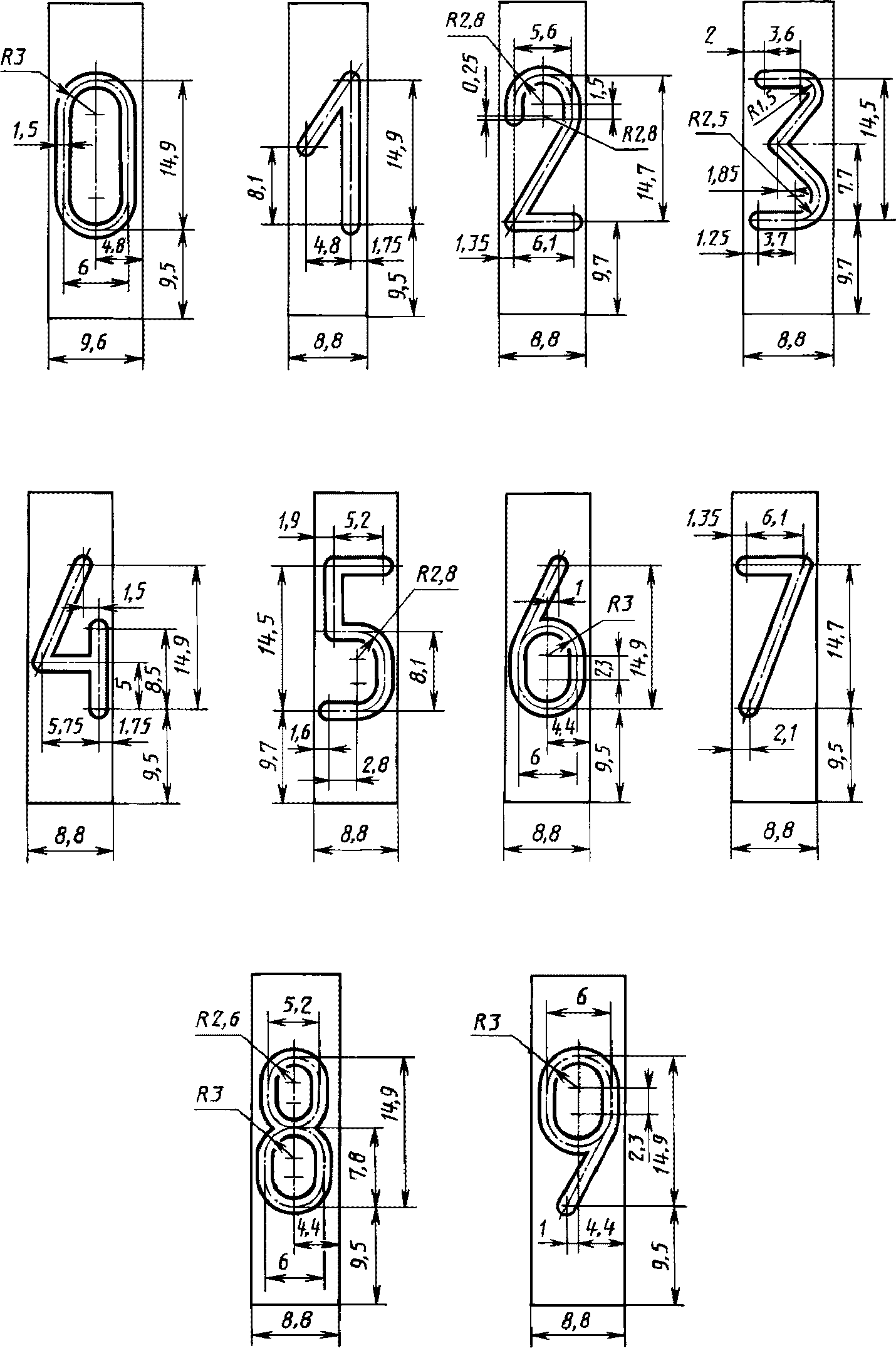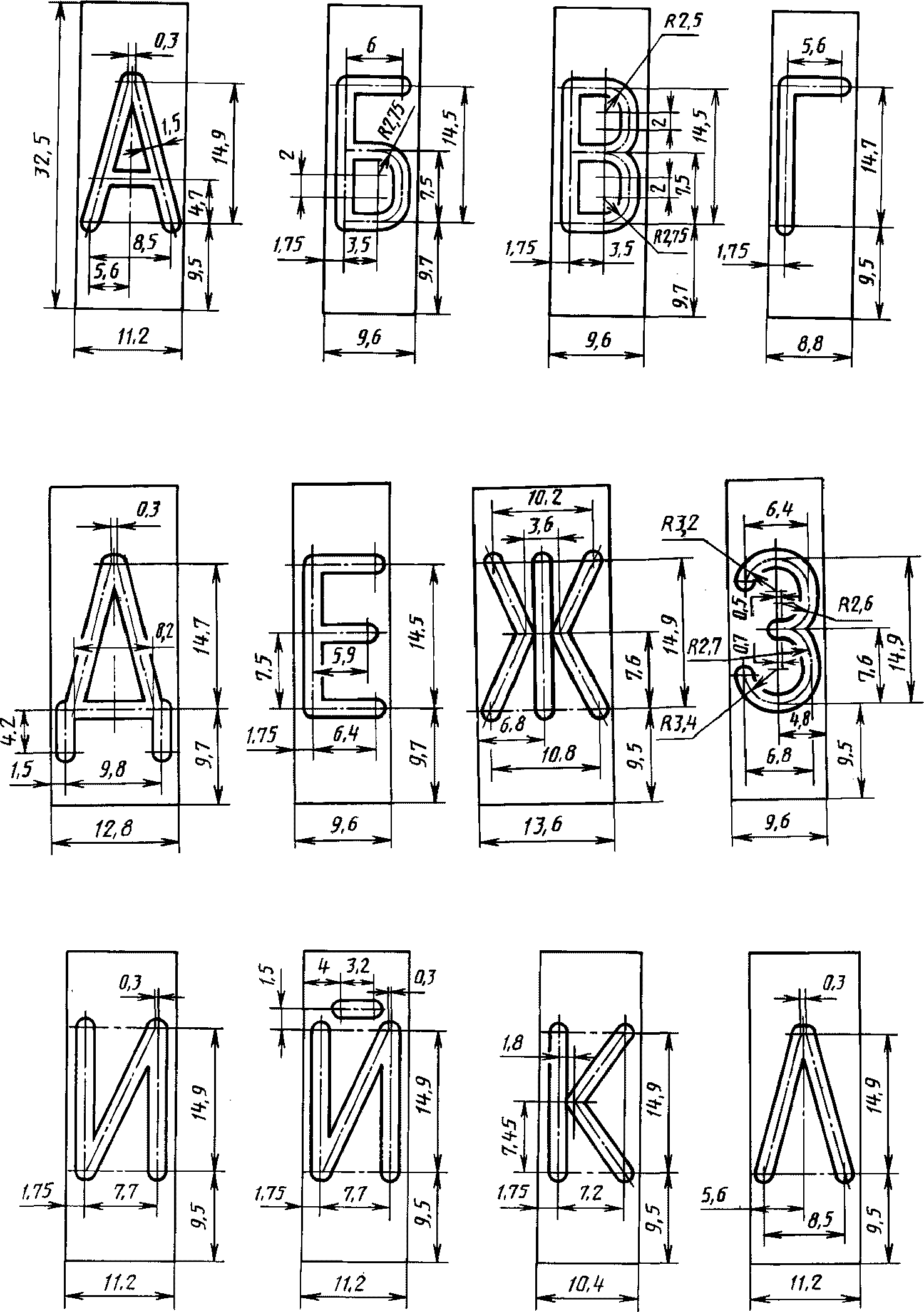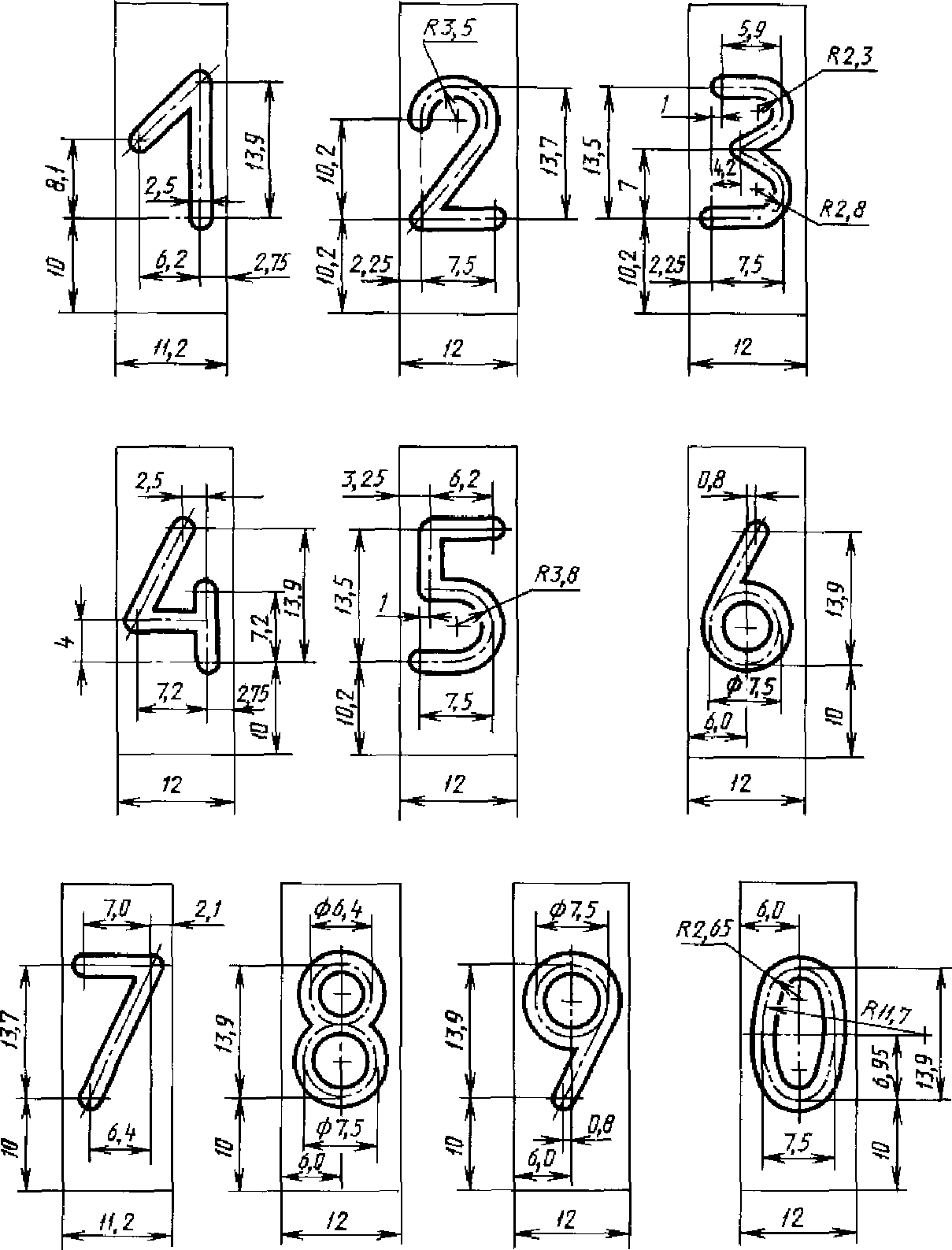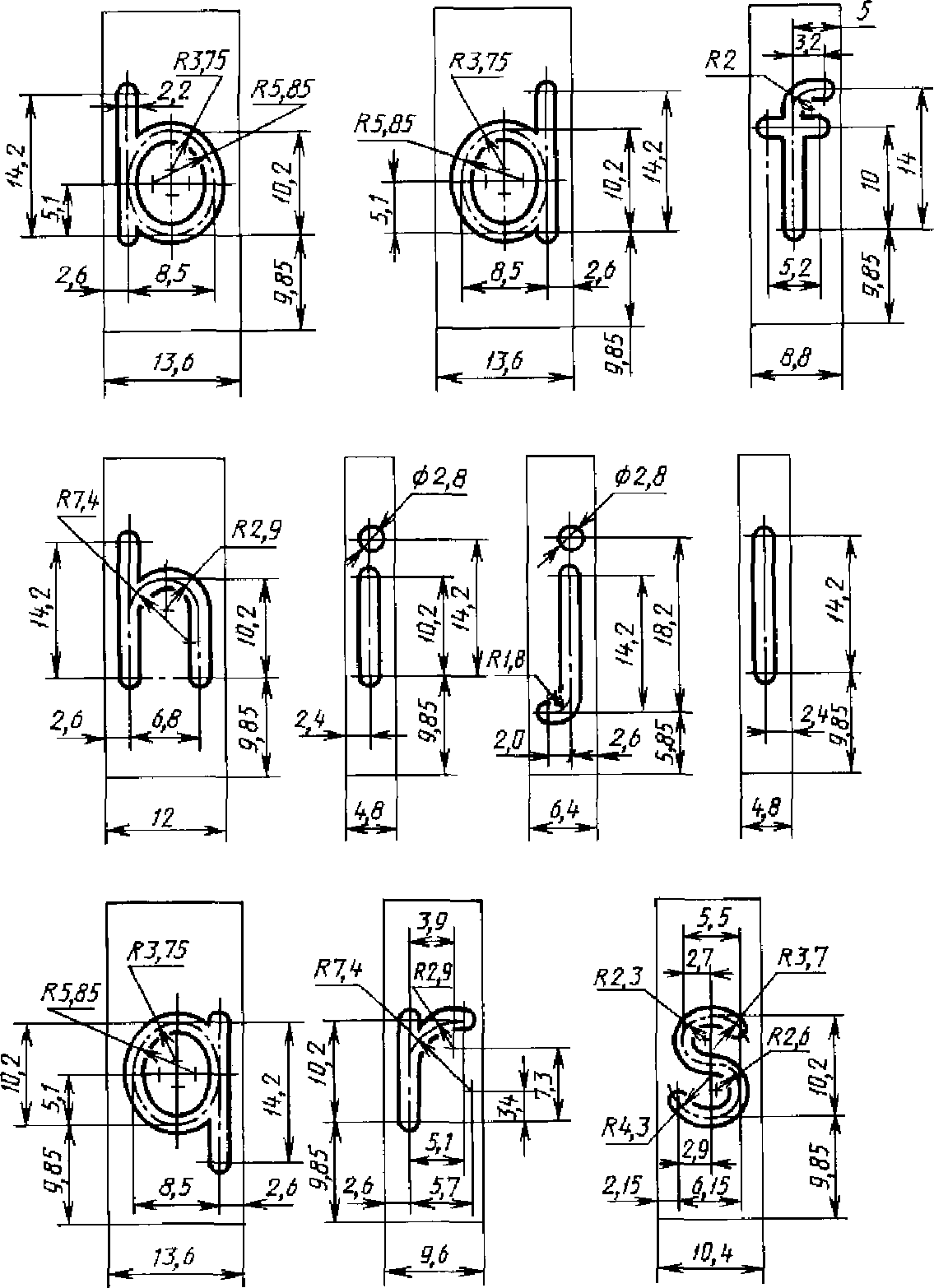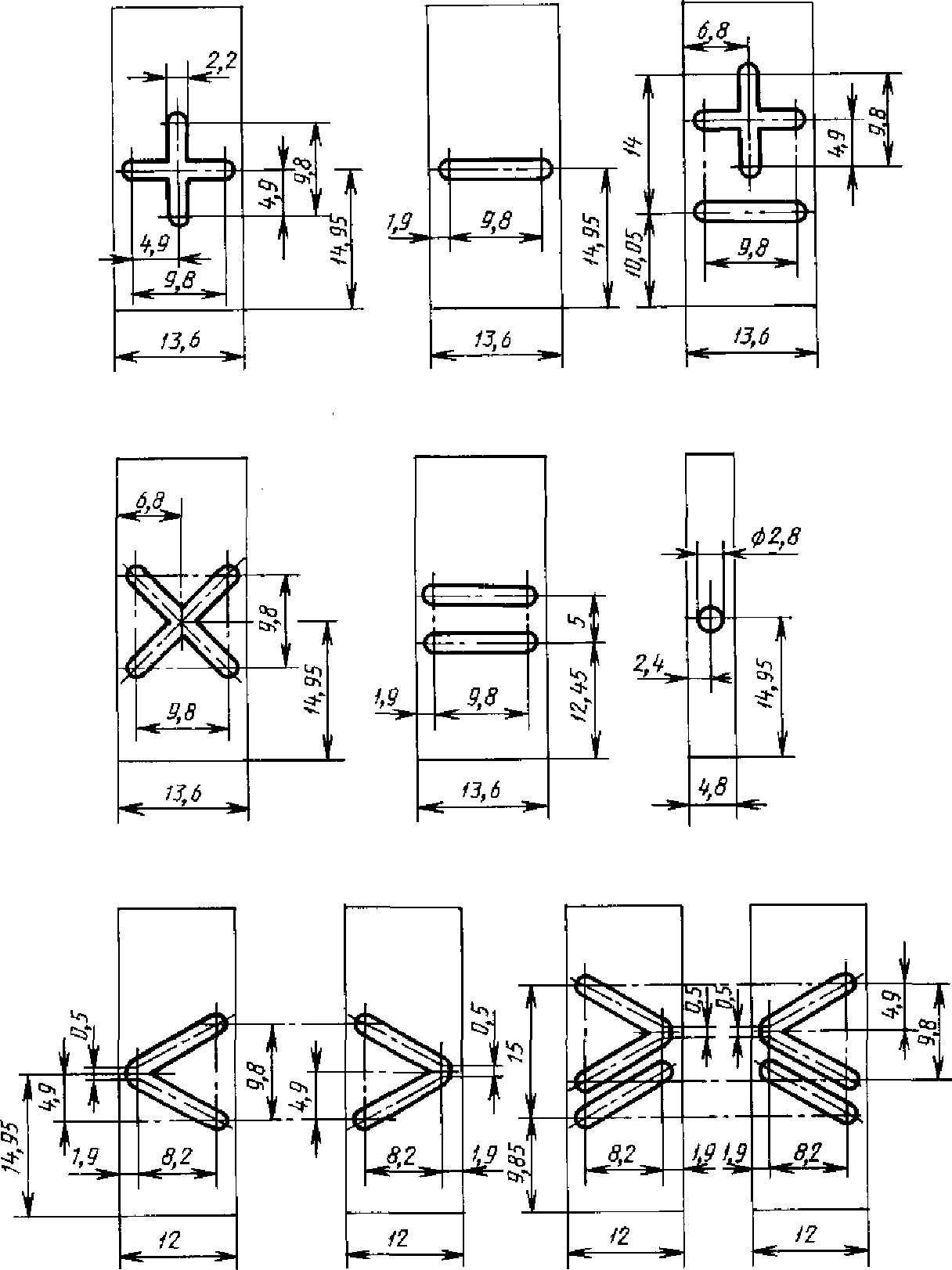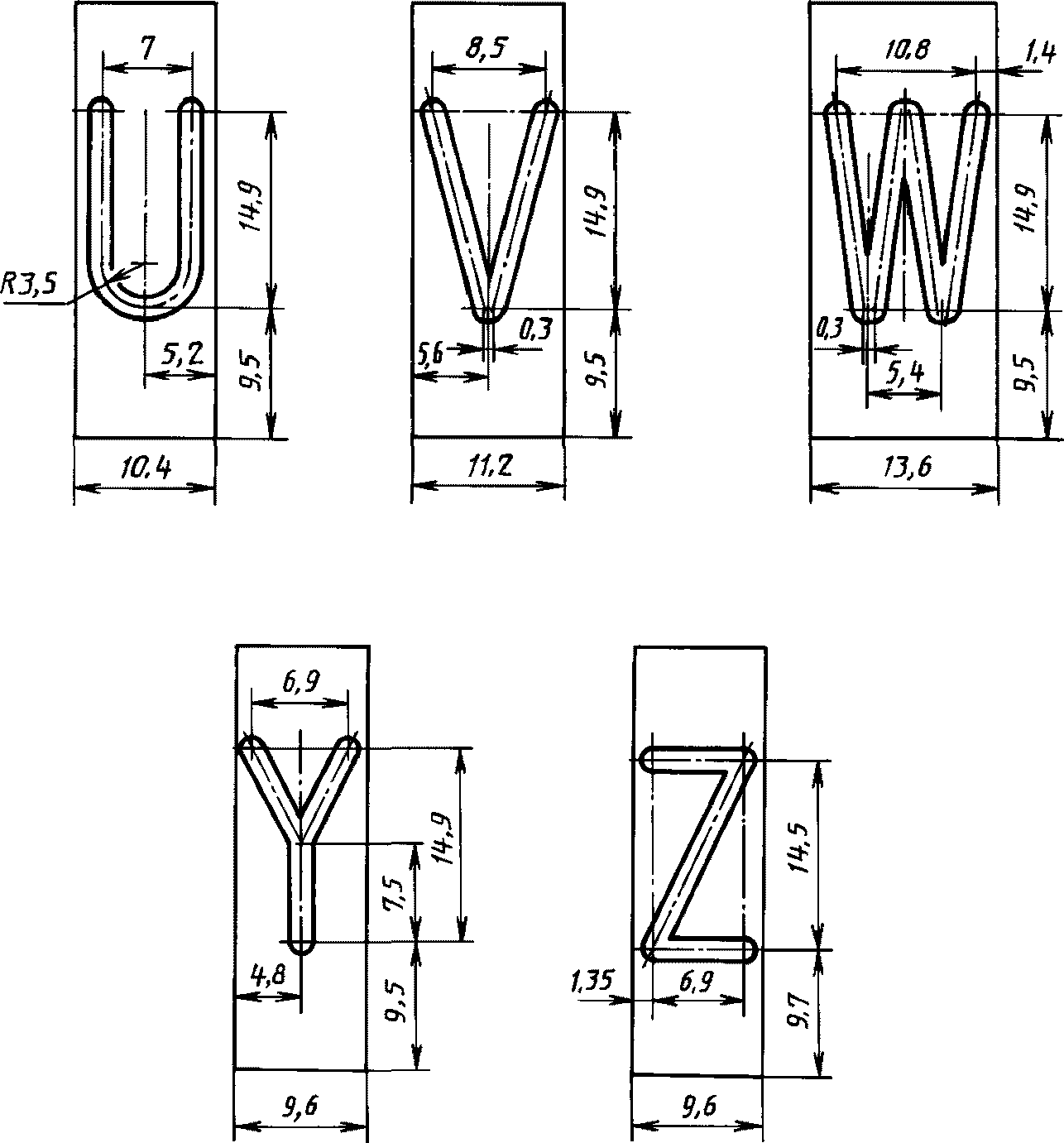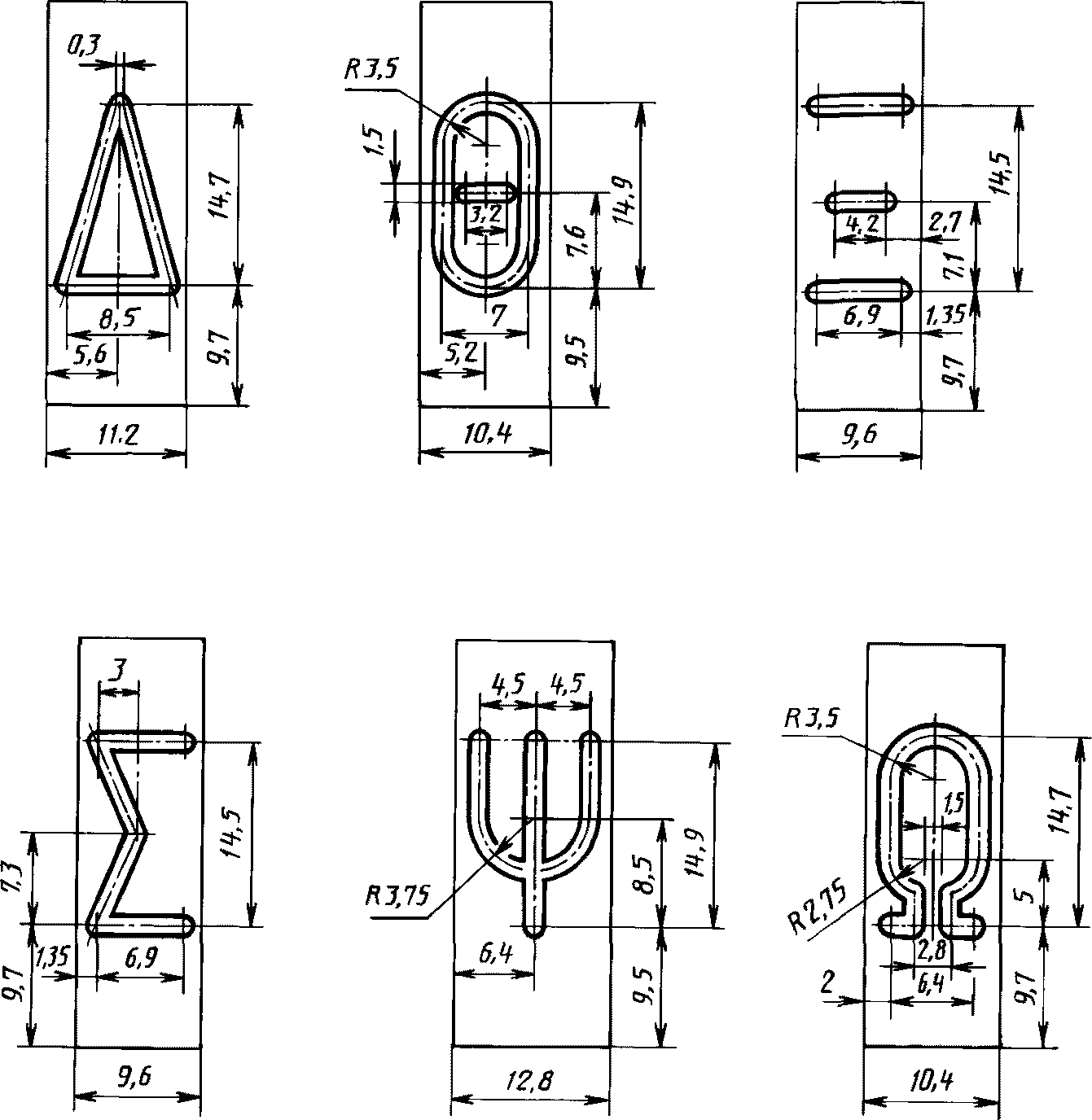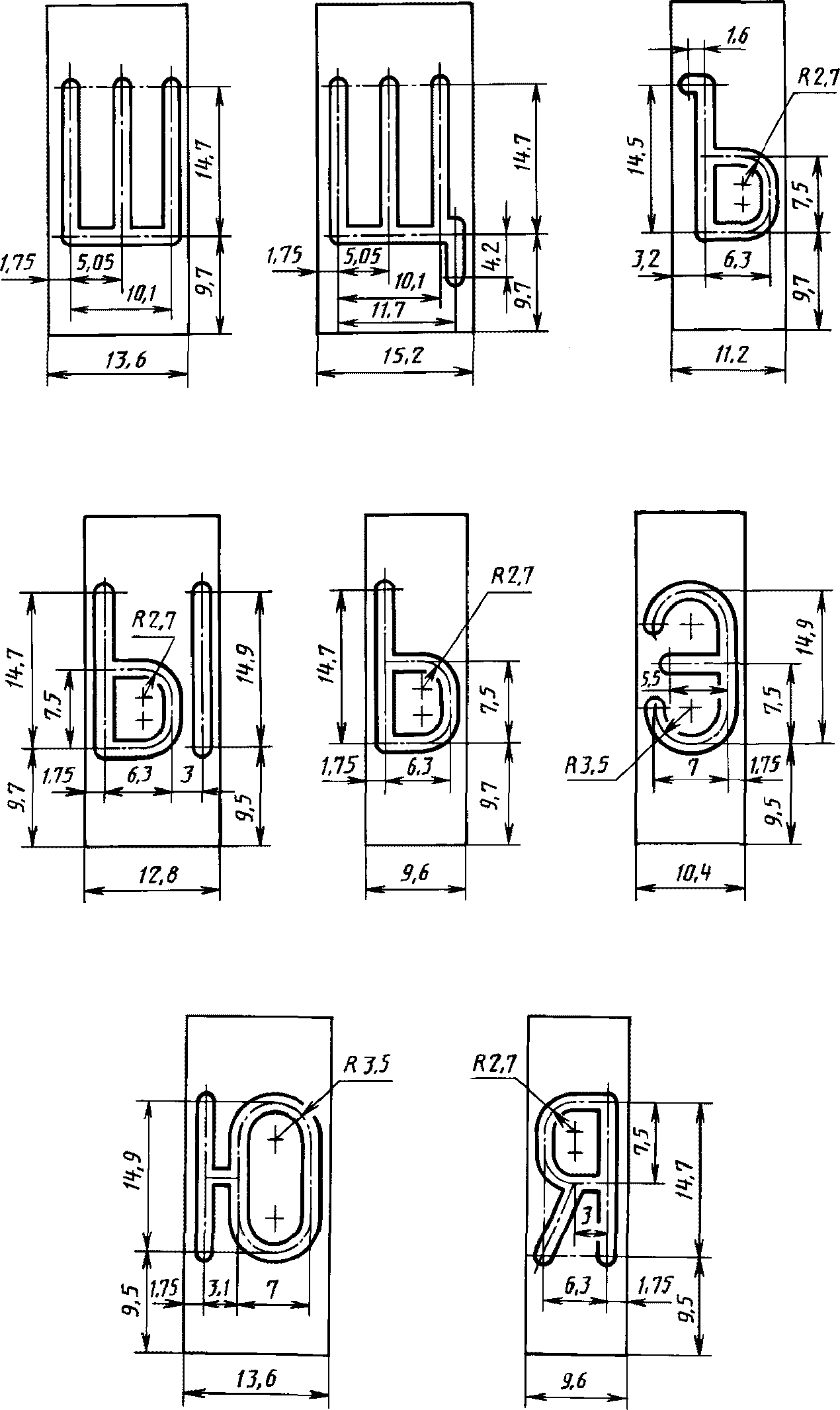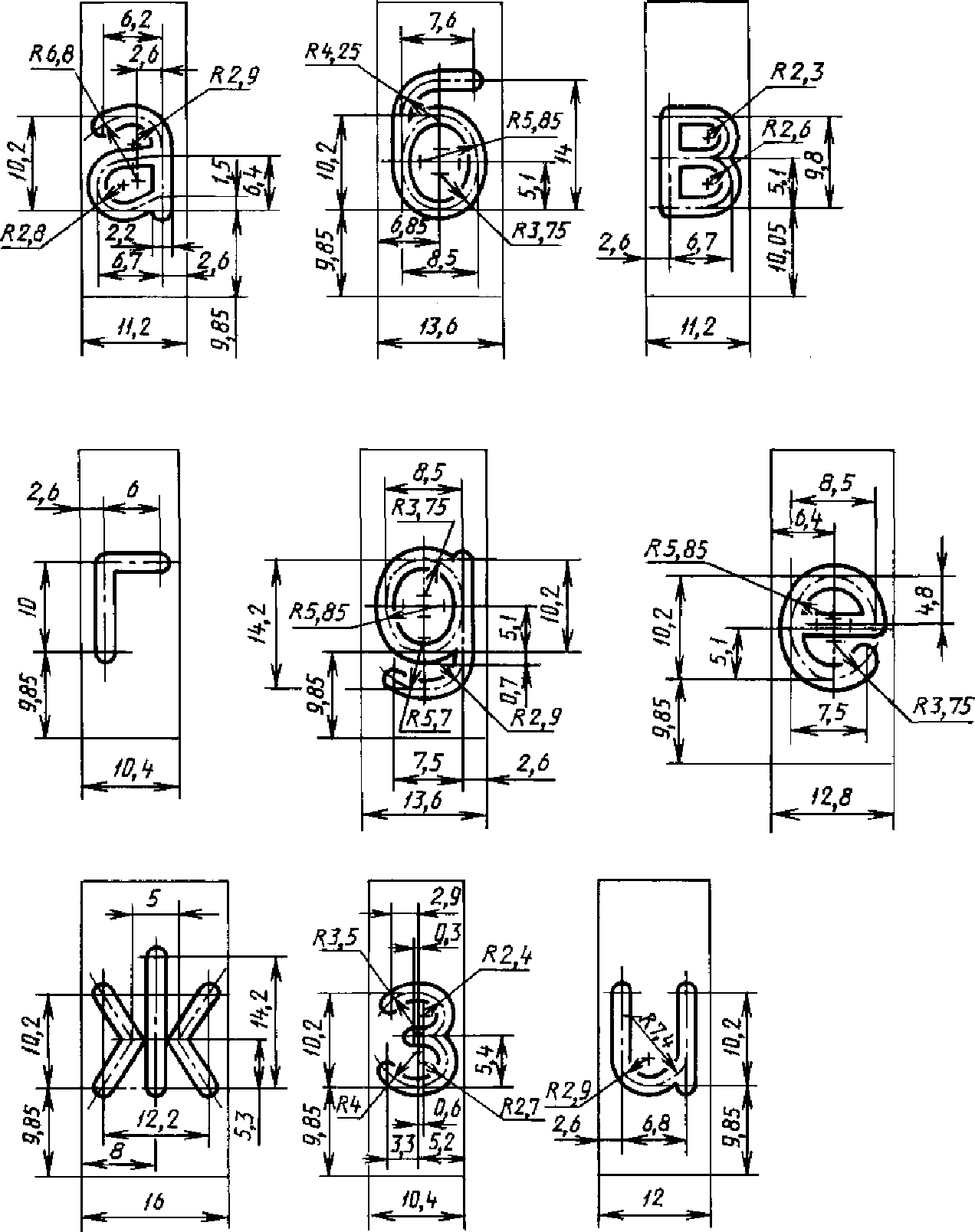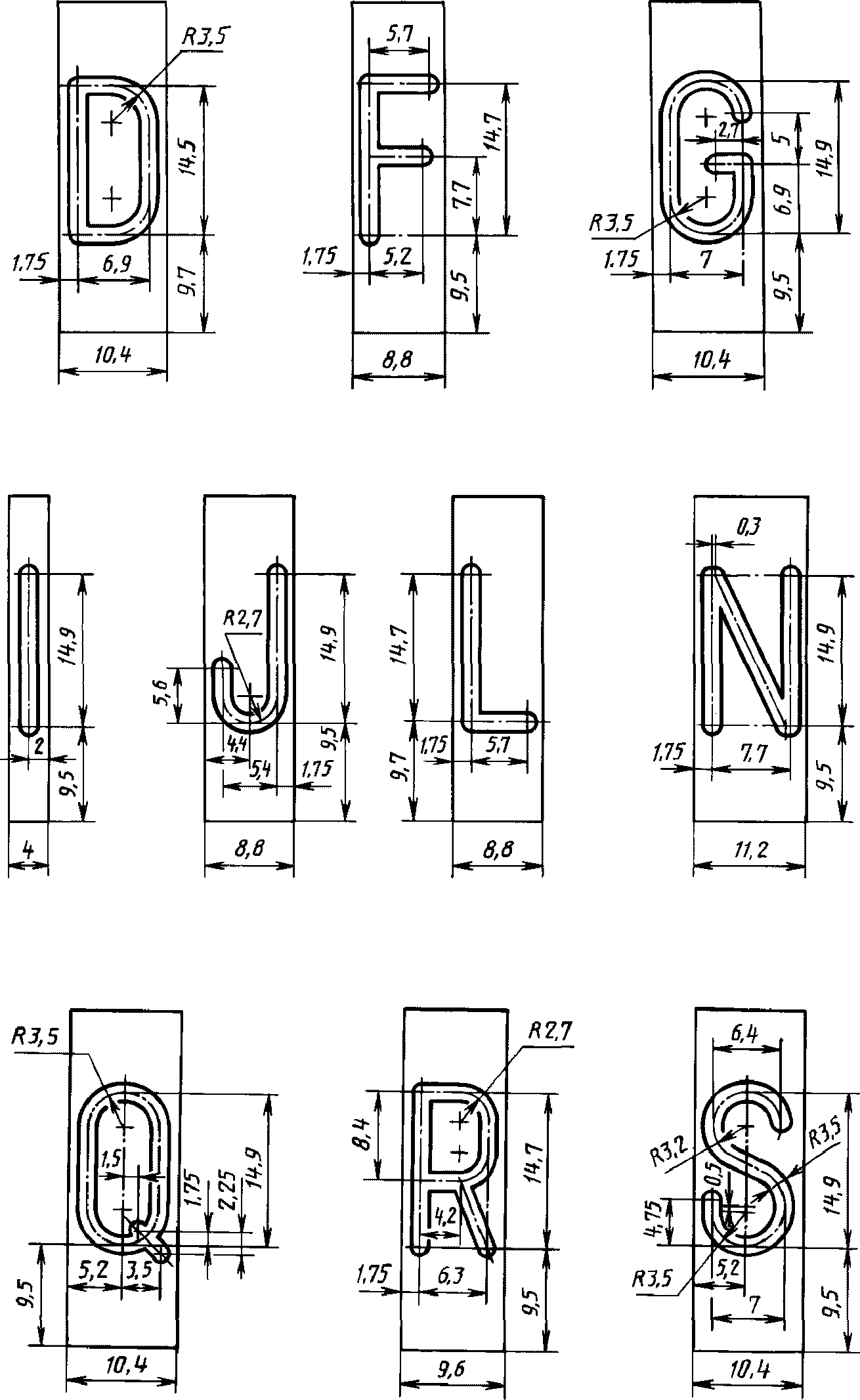
"ГОСТ 26.008-85. Межгосударственный стандарт. Шрифты для надписей, наносимых методом гравирования. Исполнительные размеры"
МЕЖГОСУДАРСТВЕННЫЙ СТАНДАРТ
ШРИФТЫ ДЛЯ НАДПИСЕЙ, НАНОСИМЫХ МЕТОДОМ ГРАВИРОВАНИЯ
ИСПОЛНИТЕЛЬНЫЕ РАЗМЕРЫ
Lettering for inscriptions applied by engraving
method. Executive dimensions
ГОСТ 26.008-85
Настоящий стандарт распространяется на шрифты приборной гарнитуры по
ГОСТ 26.020 (далее - шрифты) начертаний Пр3 (прямого нормального полужирного) и Пр41 (прямого узкого светлого) для нанесения надписей методом гравирования на средства измерений и автоматизации, радиоэлектронную аппаратуру, вычислительную технику и другие изделия.
Шрифты допускается использовать также для нанесения надписей другими методами, требующими построения отдельных элементов букв, цифр, знаков по размерам.
Все требования настоящего стандарта являются обязательными.
Для изделий, разработанных до 01.01.87, допускается использовать шрифты по
ГОСТ 2930.
При нанесении надписей методами, не требующими построения по размерам, следует руководствоваться
ГОСТ 26.020.
Шрифты и требования по нанесению надписей методами гравирования на изделия авиационного приборостроения могут быть установлены согласно требованиям нормативно-технических документов на указанные изделия, отличным от требований настоящего стандарта.
(Измененная редакция, Изм. N 3).
1.1. В состав шрифта начертания Пр3 входят: прописные и строчные буквы русского, латинского и греческого алфавитов; арабские и римские цифры; знаки препинания; математические знаки.
В состав шрифта начертания Пр41 входят: прописные буквы русского, латинского, греческого алфавитов; арабские цифры.
1.2. Примеры условного обозначения шрифта высотой 5 мм начертания Пр3:
Шрифт 5 - Пр3 ГОСТ 26.008-85
высотой 4 мм начертания Пр41:
Шрифт 4 - Пр41 ГОСТ 26.008-85.
1.1, 1.2. (Измененная редакция, Изм. N 3).
2. НАЧЕРТАНИЕ И РАЗМЕРЫ ШРИФТОВ
2.1. Для нанесения надписей на изделия методом гравирования принят шрифт высотой H: 1,0; 1,2; 1,6; 2,0; 2,5; 3,0; 4,0; 5,0; 6,0; 8,0; 10,0; 12,0; 16,0 мм. Допускается применять шрифты высотой H: 0,6; 0,8; 20,0; 25,0; 30,0; 40,0; 50,0; 60,0; 80,0; 100,0 мм.
2.2. Основные размеры шрифта должны соответствовать указанным на черт. 1.
1 - линия шрифта; H - высота шрифта; b, b1 - толщина
обводки; h - высота букв строчных; K - высота площадки
до линии шрифта;
= 0,2 мм для шрифта высотой
H = 16 мм; Ti - ширина площадки
Черт. 1
Размер шрифта, характеризуемый высотой
H, определяет размер прописных букв
Б, В, Е, D,
,
.
2.3. Для гравирования шрифтов на копировальных планках рекомендована высота шрифта
H = 16 мм. Состав, конфигурация и исполнительные размеры шрифта Пр3 указаны в
приложении 1, шрифта Пр41 - в
приложении 1а.
Исполнительные размеры шрифтов высотой, отличной от H = 16 мм, получают путем пропорционального уменьшения или увеличения размеров шрифта высотой H = 16 мм.
2.2, 2.3. (Измененная редакция, Изм. N 3).
2.4. Размеры профиля гравировки шрифтов должны соответствовать указанным на черт. 2.
Черт. 2
Примечание. Допускается профиль гравирования (угол и радиус скругления для
b <= 1 мм), заполняемый краской, не регламентировать при выполнении условия
.
(Измененная редакция, Изм. N 1).
3. УКАЗАНИЯ ПО ПОСТРОЕНИЮ НАДПИСЕЙ И ПРАВИЛА ГРАВИРОВАНИЯ
3.1. Указания по изготовлению и применению копировальных гравировальных планок приведены в
приложении 2.
3.2. Интервалы между буквами, цифрами, знаками в словах обеспечиваются шириной копировальных планок (площадок) Ti. При сочетании букв типа ГА, ГД, ГЛ, ТА, УЛ и т.п. интервалы допускается сокращать.
(Измененная редакция, Изм. N 2).
3.3. Расстояние между строками устанавливают равным 0,5 высоты шрифта H.
3.4. Интервалы между буквами, цифрами и знаками, расстояния между словами и расстояния между строками допускается изменять, исходя из композиционных соображений.
(Измененная редакция, Изм. N 2).
3.5. Коэффициент уменьшения шрифта (K) выражается формулой
где H - высота шрифта на копировальной планке, равная 16 мм;
A - размер элемента буквы, цифры, знака шрифта высотой 16 мм, указанный в
приложении 1,
1а, мм;
H1 - высота шрифта надписи на изделии, мм.
Числовые значения коэффициентов уменьшения, толщины обводки шрифта и расстояния между словами в зависимости от заданной высоты шрифта приведены в таблице. Расстояния между словами установлены равными ширине площадки прописных букв Н или П.
Высота шрифта H, мм | 1,0 | 1,2 | 1,6 | 2,0 | 2,5 | 3,0 | 4,0 | 5,0 | 6,0 | 8,0 | 10,0 | 12,0 | 16,0 |
Коэффициент уменьшения K | 16,00 | 13,33 | 10,00 | 8,00 | 6,40 | 5,33 | 4,00 | 3,20 | 2,67 | 2,00 | 1,60 | 1,33 | 1,00 |
Шрифт Пр3 | Толщина обводки шрифта b, мм | прописного | 0,16 | 0,19 | 0,25 | 0,31 | 0,40 | 0,47 | 0,62 | 0,80 | 0,94 | 1,25 | 1,60 | 1,88 | 2,50 |
строчного | 0,14 | 0,17 | 0,22 | 0,28 | 0,34 | 0,41 | 0,55 | 0,69 | 0,88 | 1,10 | 1,38 | 1,65 | 2,20 |
Расстояние между словами, мм | 1,0 | 1,10 | 1,50 | 1,90 | 2,40 | 2,90 | 3,80 | 4,80 | 5,70 | 7,60 | 9,50 | 11,40 | 15,2 |
Шрифт Пр41 | Толщина обводки шрифта b, мм | 0,10 | 0,10 | 0,20 | 0,20 | 0,20 | 0,30 | 0,40 | 0,50 | 0,60 | 0,80 | 0,90 | 1,1 | 1,5 |
Расстояние между словами, мм | 0,70 | 0,80 | 1,00 | 1,30 | 1,60 | 2,00 | 2,60 | 3,60 | 3,90 | 5,20 | 6,50 | 7,4 | 10,4 |
(Измененная редакция, Изм. N 3).
4.1. Предельные отклонения от номинального размера толщины обводки букв, цифр и знаков не должны превышать +/- 15% для b <= 2 мм; +/- 10% для b > 2 мм.
(Измененная редакция, Изм. N 3).
4.2. Разница в толщине обводки шрифта в пределах одной надписи не должна превышать следующих значений:
для толщин обводки b <= 0,5 мм - 10%;
для толщин обводки b > 0,5 мм - 6%.
4.3. Предельные отклонения размеров букв, цифр и знаков по высоте, размеров, определяющих положение букв, цифр и знаков на копировальных планках и шаблонах, на панелях и других изделиях, размеров между буквами, цифрами и знаками, словами и строками - для размеров, равных 1 мм и менее +/- 0,2 мм; для размеров свыше 1 мм - по
при нанесении надписи на металле; по
при нанесении надписи на пластическом материале (оргстекло, гетинакс и др.).
(Измененная редакция, Изм. N 2, 3).
4.4. Размеры букв, цифр и знаков, расстояния между словами и строками и их предельные отклонения для копировальных шаблонов необходимо указывать на чертежах копировальных шаблонов.
(Измененная редакция, Изм. N 2).
Обязательное
ИСПОЛНИТЕЛЬНЫЕ РАЗМЕРЫ ШРИФТА Пр3 ВЫСОТОЙ
H = 16 ММ
НА КОПИРОВАЛЬНЫХ ПЛАНКАХ
Прописные латинские буквы
Прописные греческие буквы
Знаки препинания, математические знаки
ПРИЛОЖЕНИЕ 1. (Измененная редакция, Изм. N 2, 3).
Обязательное
ИСПОЛНИТЕЛЬНЫЕ РАЗМЕРЫ ШРИФТА Пр41 ВЫСОТОЙ
H = 16 ММ
НА КОПИРОВАЛЬНЫХ ПЛАНКАХ
Прописные латинские буквы
Прописные греческие буквы
Рекомендуемое
ПО ИЗГОТОВЛЕНИЮ И ПРИМЕНЕНИЮ КОПИРОВАЛЬНЫХ
ГРАВИРОВАЛЬНЫХ ПЛАНОК
1. Конструкция и размеры копировальных планок для всех букв, цифр, знаков, кроме знака
, приведены на
черт. 1. Конструкция и размеры копировальной планки для знака
приведены на
черт. 1а.
Номинальный размер ширины планки равен ширине площадки Ti. Предельные отклонения, мм, на ширину планки Ti, мм:
для
св. 3 до 6 включ. +0,155,
+0,035;
" " " 6 " 10 " +0,192,
+0,042;
" " " 10 " 14 " +0,230,
+0,050;
" " " 14 " 18 " +0,240,
+0,060;
" " " 18 " 24 " +0,283,
+0,073;
" " " 24 " 30 " +0,298;
+0,088.
ПРИЛОЖЕНИЕ 2. (Измененная редакция, Изм. N 3).
2. Расположение шрифтов на планках с указанием привязочных размеров приведено на чертежах в
приложении 1.
3. Размеры профиля гравировки шрифтов на планках указаны на черт. 2.
Черт. 2
(Измененная редакция, Изм. N 2).
4. Шрифты на планках выполняются вручную или по копирам.
5. Планки предназначены для нанесения надписей методом гравирования на копировально-фрезерных (гравировальных) станках как непосредственно на изделиях, так и на копировальные шаблоны.
6. Надписи составляют путем набора копировальных планок с соответствующими буквами, цифрами и знаками.
Копировальные планки устанавливают вплотную в паз стола копировально-фрезерного (гравировального) станка.
7. Если надпись предназначена для многократного нанесения на изделие, то рекомендуется по копировальным планкам изготовить копировальный шаблон на эту надпись. Этот шаблон служит копиром для гравирования надписи на копировально-фрезерных (гравировальных) станках.
8. При гравировании надписей на копировально-фрезерных (гравировальных) станках по копировальным планкам или копировальным шаблонам в надписях периодически проверяются только размеры шрифта по высоте и толщине обводки и размеры между словами и строками.
Обязательное
ЗНАЧЕНИЯ ШИРИНЫ ПЛОЩАДОК
Ti ДЛЯ ШРИФТА Пр3
Буква, цифра, знак | Ширина площадки Ti для шрифта высотой H, мм |
1,0 | 1,2 | 1,6 | 2,0 | 2,5 | 3,0 | 4,0 | 5,0 | 6,0 | 8,0 | 10,0 | 12,0 | 16,0 |
| 0,3 | 0,4 | 0,5 | 0,6 | 0,8 | 0,9 | 1,2 | 1,5 | 1,8 | 2,4 | 3,0 | 3,6 | 4,8 |
| 0,4 | 0,4 | 0,6 | 0,7 | 0,9 | 1,1 | 1,4 | 1,8 | 2,1 | 2,8 | 3,5 | 4,2 | 5,6 |
| 0,4 | 0,5 | 0,6 | 0,8 | 1,0 | 1,2 | 1,6 | 2,0 | 2,4 | 3,2 | 4,0 | 4,8 | 6,4 |
| 0,5 | 0,5 | 0,7 | 0,9 | 1,1 | 1,4 | 1,8 | 2,3 | 2,7 | 3,6 | 4,5 | 5,4 | 7,2 |
| 0,6 | 0,7 | 0,9 | 1,1 | 1,4 | 1,7 | 2,2 | 2,8 | 3,3 | 4,4 | 5,5 | 6,6 | 8,8 |
| 0,6 | 0,7 | 1,0 | 1,2 | 1,5 | 1,8 | 2,4 | 3,0 | 3,6 | 4,8 | 6,0 | 7,2 | 9,6 |
| 0,7 | 0,8 | 1,0 | 1,3 | 1,6 | 2,0 | 2,6 | 3,3 | 3,9 | 5,2 | 6,5 | 7,8 | 10,4 |
| 0,7 | 0,8 | 1,1 | 1,4 | 1,8 | 2,1 | 2,8 | 3,5 | 4,2 | 5,6 | 7,0 | 8,4 | 11,2 |
| 0,8 | 0,9 | 1,2 | 1,5 | 1,9 | 2,3 | 3,0 | 3,8 | 4,5 | 6,0 | 7,5 | 9,0 | 12,0 |
| 0,8 | 1,0 | 1,3 | 1,6 | 2,0 | 2,4 | 3,2 | 4,0 | 4,8 | 6,4 | 8,0 | 9,6 | 12,8 |
| 0,9 | 1,0 | 1,4 | 1,7 | 2,1 | 2,6 | 3,4 | 4,3 | 5,1 | 6,8 | 8,5 | 10,2 | 13,6 |
| 0,9 | 1,1 | 1,4 | 1,8 | 2,3 | 2,7 | 3,6 | 4,5 | 5,4 | 7,2 | 9,0 | 10,8 | 14,4 |
| 1,0 | 1,1 | 1,5 | 1,9 | 2,4 | 2,9 | 3,8 | 4,8 | 5,7 | 7,6 | 9,5 | 11,4 | 15,2 |
| 1,0 | 1,2 | 1,6 | 2,0 | 2,5 | 3,0 | 4,0 | 5,0 | 6,0 | 8,0 | 10,0 | 12,0 | 16,0 |
| 1,1 | 1,3 | 1,7 | 2,1 | 2,6 | 3,2 | 4,2 | 5,3 | 6,3 | 8,4 | 10,5 | 12,6 | 16,8 |
| 1,1 | 1,3 | 1,8 | 2,2 | 2,9 | 3,3 | 4,4 | 5,5 | 6,6 | 8,8 | 11,0 | 13,2 | 17,6 |
| 1,2 | 1,4 | 1,8 | 2,3 | 2,9 | 3,5 | 4,6 | 5,8 | 6,9 | 9,2 | 11,5 | 13,8 | 18,4 |
| 1,2 | 1,4 | 1,9 | 2,4 | 3,0 | 3,6 | 4,8 | 6,0 | 7,2 | 9,6 | 12,0 | 14,4 | 19,2 |
| 1,3 | 1,5 | 2,0 | 2,5 | 3,1 | 3,8 | 5,0 | 6,3 | 7,5 | 10,0 | 12,5 | 15,0 | 20,0 |
| 1,3 | 1,6 | 2,1 | 2,6 | 3,3 | 3,9 | 5,2 | 6,5 | 7,8 | 10,4 | 13,0 | 15,6 | 20,8 |
| 1,4 | 1,6 | 2,2 | 2,7 | 3,4 | 4,1 | 5,4 | 6,8 | 8,1 | 10,8 | 13,5 | 16,2 | 21,6 |
| 1,4 | 1,7 | 2,2 | 2,8 | 3,5 | 4,2 | 5,6 | 7,0 | 8,4 | 11,2 | 14,0 | 16,8 | 22,4 |
| 1,5 | 1,8 | 2,4 | 3,0 | 3,8 | 4,5 | 6,0 | 7,5 | 9,0 | 12,0 | 15,0 | 18,0 | 24,0 |
| 1,7 | 2,0 | 2,7 | 3,4 | 4,3 | 5,1 | 6,8 | 8,5 | 10,2 | 13,6 | 17,0 | 20,4 | 27,2 |
| 1,8 | 2,1 | 2,8 | 3,5 | 4,4 | 5,3 | 7,0 | 8,8 | 10,5 | 14,0 | 17,5 | 21,0 | 28,0 |
ПРИЛОЖЕНИЕ 3. (Измененная редакция, Изм. N 2, 3).
Обязательное
ЗНАЧЕНИЯ ШИРИНЫ ПЛОЩАДОК T ДЛЯ ШРИФТА Пр41
Буква, цифра, знак | Высота шрифта H, мм |
1,0 | 1,2 | 1,6 | 2,0 | 2,5 | 3,0 | 4,0 | 5,0 | 6,0 | 8,0 | 10,0 | 12,0 | 16,0 |
I | 0,25 | 0,3 | 0,4 | 0,5 | 0,6 | 0,8 | 1,0 | 1,3 | 1,5 | 2,0 | 2,5 | 3,0 | 4,0 |
1 | 0,5 | 0,6 | 0,8 | 1,0 | 1,3 | 1,5 | 2,0 | 2,5 | 3,0 | 4,0 | 5,0 | 6,0 | 8,0 |
| 0,6 | 0,7 | 0,9 | 1,1 | 1,4 | 1,7 | 2,2 | 2,8 | 3,3 | 4,4 | 5,5 | 6,6 | 8,8 |
| 0,6 | 0,7 | 1,0 | 1,2 | 1,5 | 1,8 | 2,4 | 3,0 | 3,6 | 4,8 | 6,0 | 7,2 | 9,6 |
| 0,7 | 0,8 | 1,0 | 1,3 | 1,6 | 2,0 | 2,6 | 3,3 | 3,9 | 5,2 | 6,5 | 7,8 | 10,4 |
| 0,7 | 0,8 | 1,1 | 1,4 | 1,8 | 2,1 | 2,8 | 3,5 | 4,2 | 5,6 | 7,0 | 8,4 | 11,2 |
| 0,8 | 1,0 | 1,3 | 1,6 | 2,0 | 2,4 | 3,2 | 4,0 | 4,8 | 6,4 | 8,0 | 9,6 | 12,8 |
| 0,9 | 1,0 | 1,4 | 1,7 | 2,1 | 2,6 | 3,4 | 4,3 | 5,1 | 6,8 | 8,5 | 10,2 | 13,6 |
Щ | 1,0 | 1,1 | 1,5 | 1,9 | 2,4 | 2,9 | 3,8 | 4,8 | 5,7 | 7,6 | 9,5 | 11,4 | 15,2 |
ПРИЛОЖЕНИЕ 4. (Введено дополнительно, Изм. N 3).